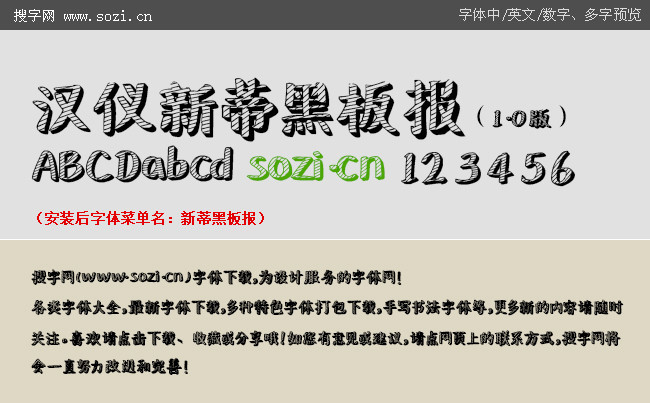
漢儀新蒂黑板報(bào)1.0
搜字網(wǎng)給大家提供一款漢儀新蒂黑板報(bào)1.0中文字體下載。漢儀新蒂黑板報(bào)體是一款卡通POP字體,由漢儀新蒂工作室出品,漢儀新蒂工作室成立于2016年,由漢儀字庫(kù)與新蒂字體聯(lián)合成立字體富有變化,字形充滿(mǎn)童趣,適合兒童產(chǎn)品畫(huà)冊(cè)、兒童產(chǎn)品包裝設(shè)計(jì)、海報(bào)設(shè)計(jì)、網(wǎng)頁(yè)標(biāo)題設(shè)計(jì)等應(yīng)用。(本字體為個(gè)人非商用版,如需要商用請(qǐng)聯(lián)系漢儀公司購(gòu)買(mǎi)版權(quán))